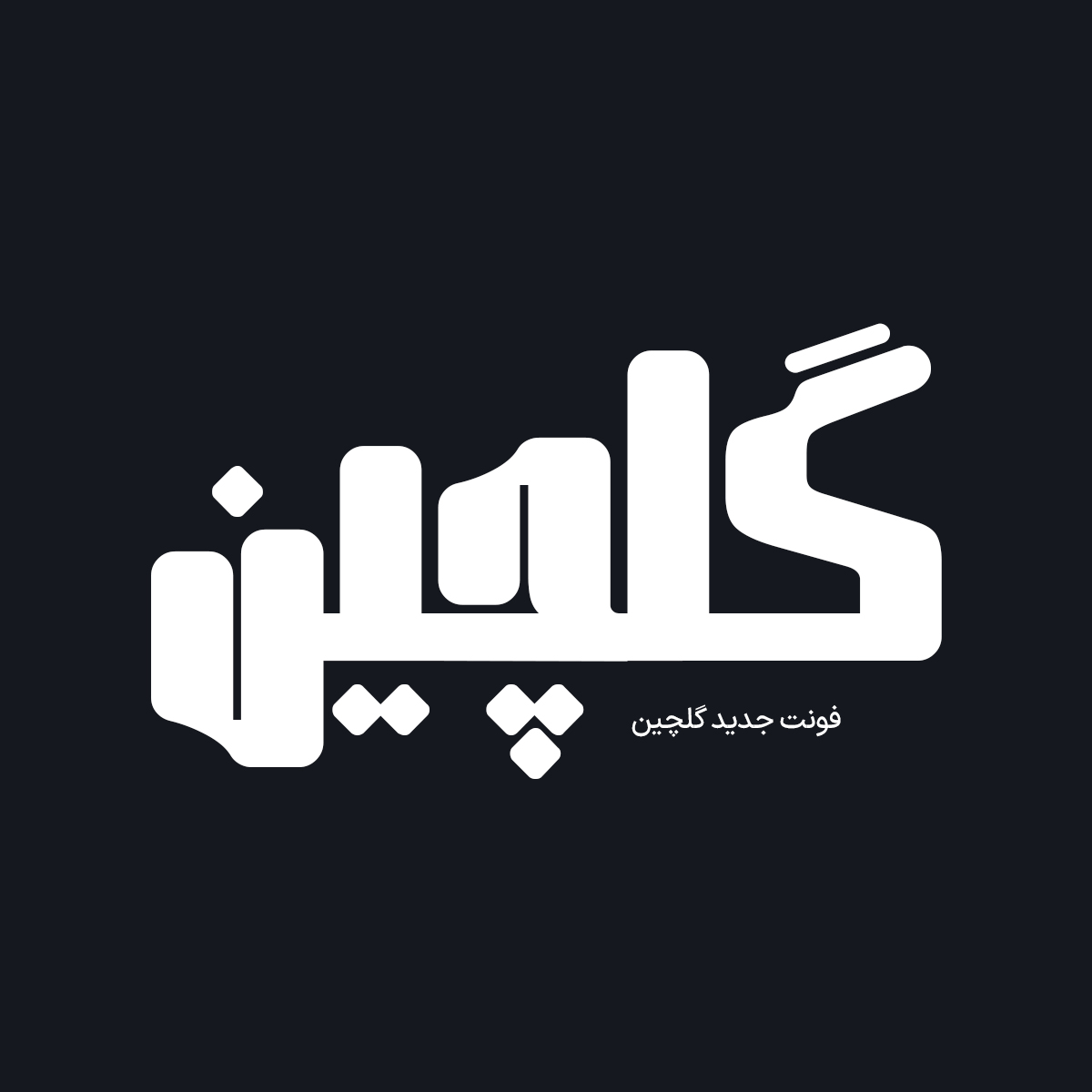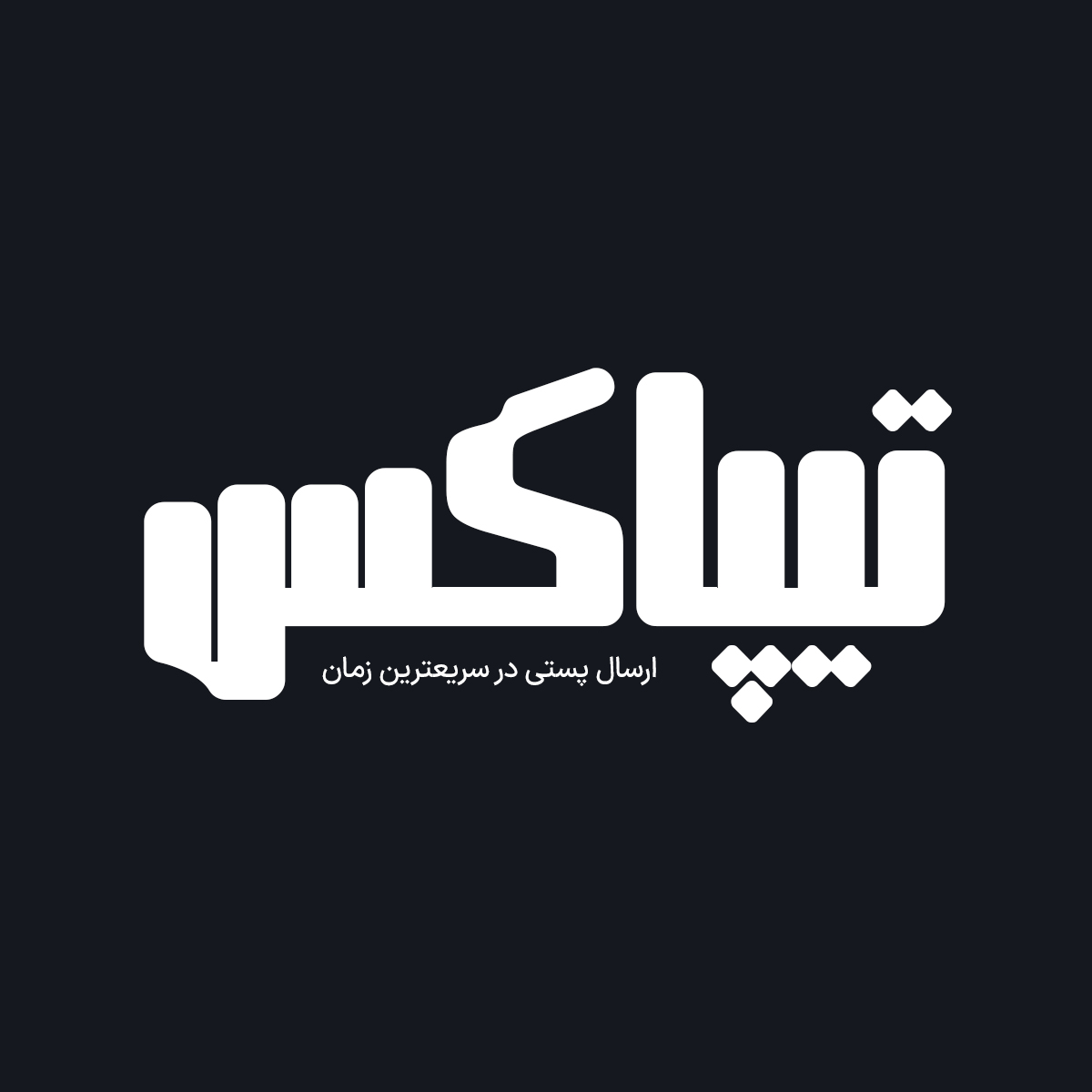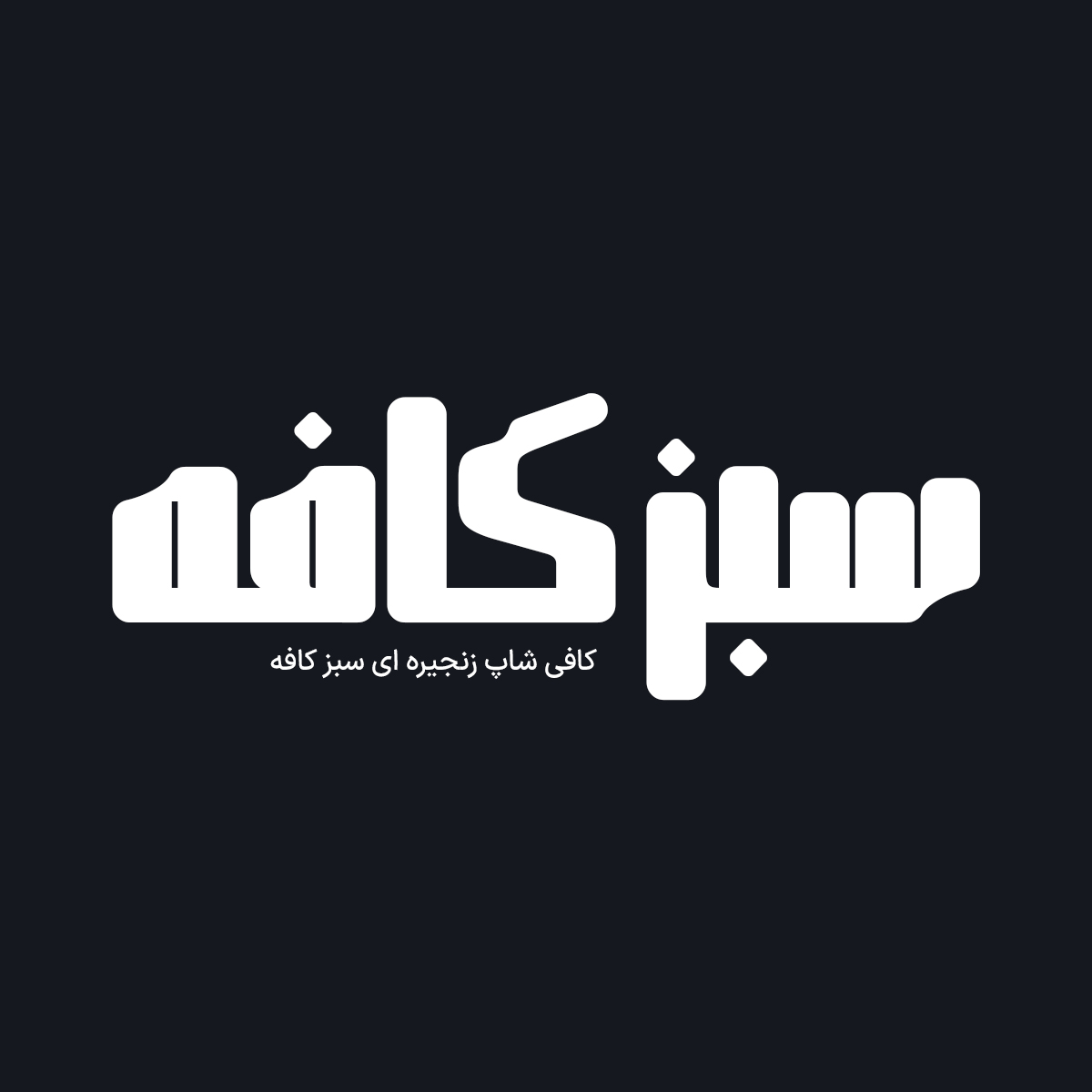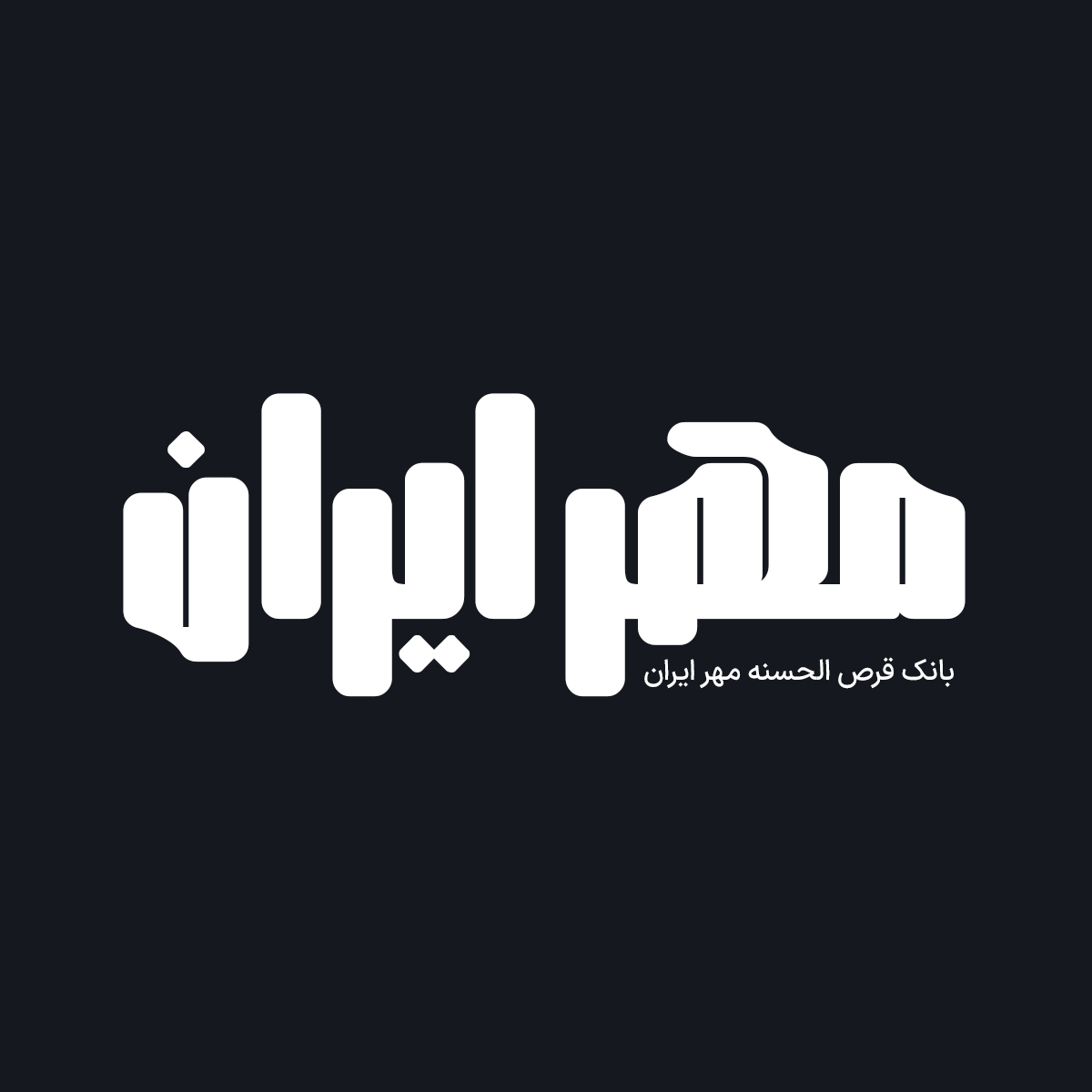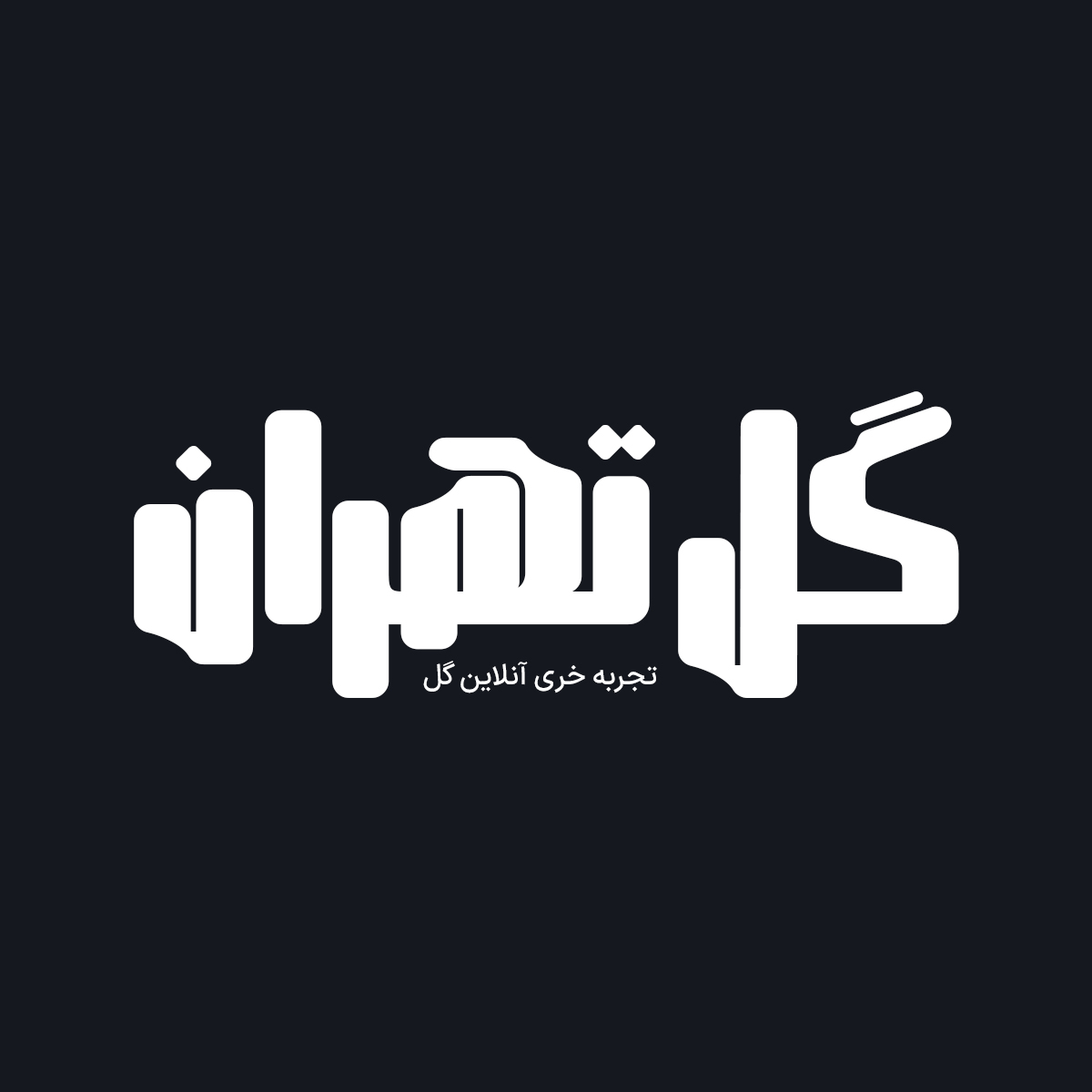
فونت فارسی گلچین یک فونت گرافیکی زیبا و حرفه ای با طراحی مدرن و خاص می باشد که حروف به نرمی و اصولی در کنار یکدیگر قرار می گیرند و شکل زیبایی از کلمات را تشکیل می دهند، فونت فارسی گلچین زیبا و حرفه ای مناسب استفاده در عناوین و تیترها و جملات نسبتا کوتاه و هم طراحی انواع لوگوتایپ، تکست گرافی و استفاده در طراحی های خاص می باشد.
پیشنمایش و نمونه تایپ های فونت گلچین